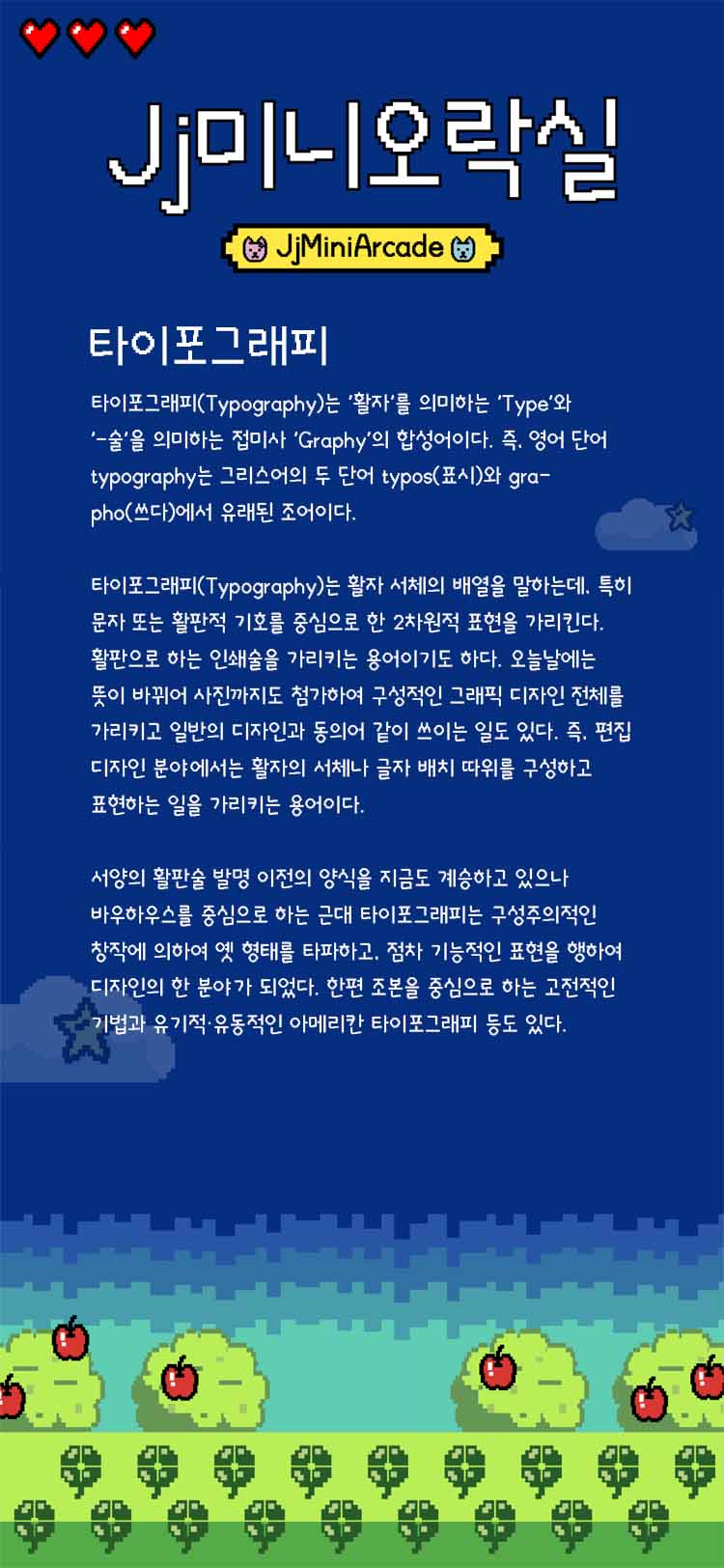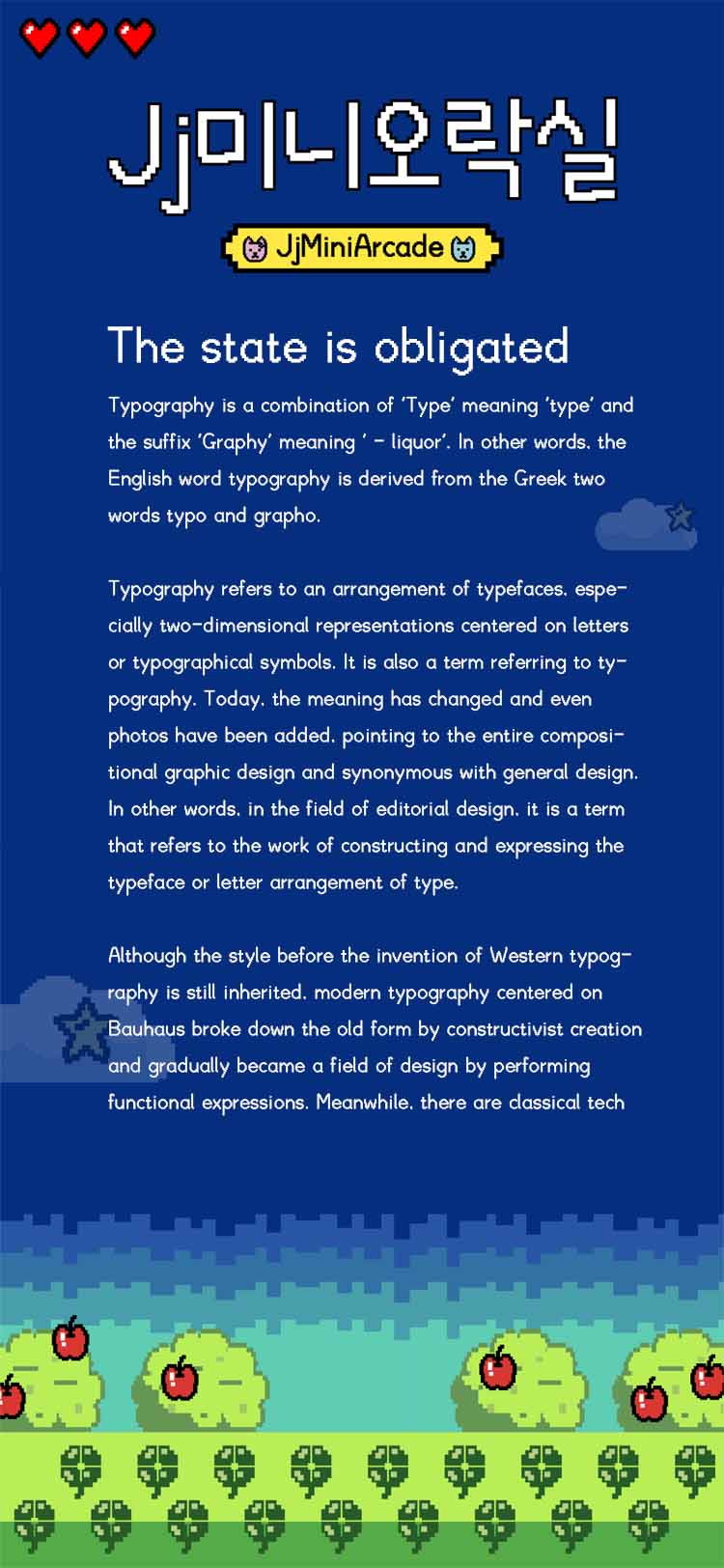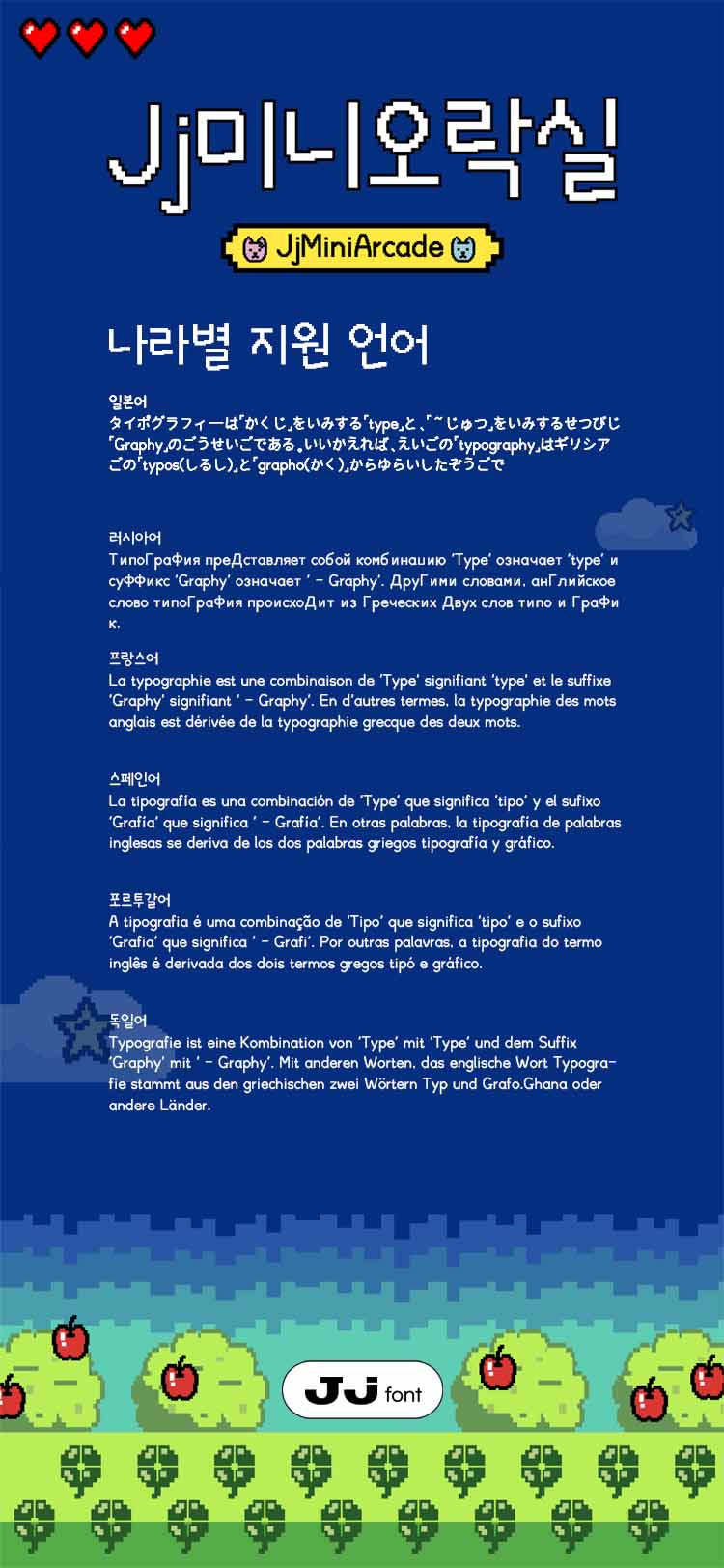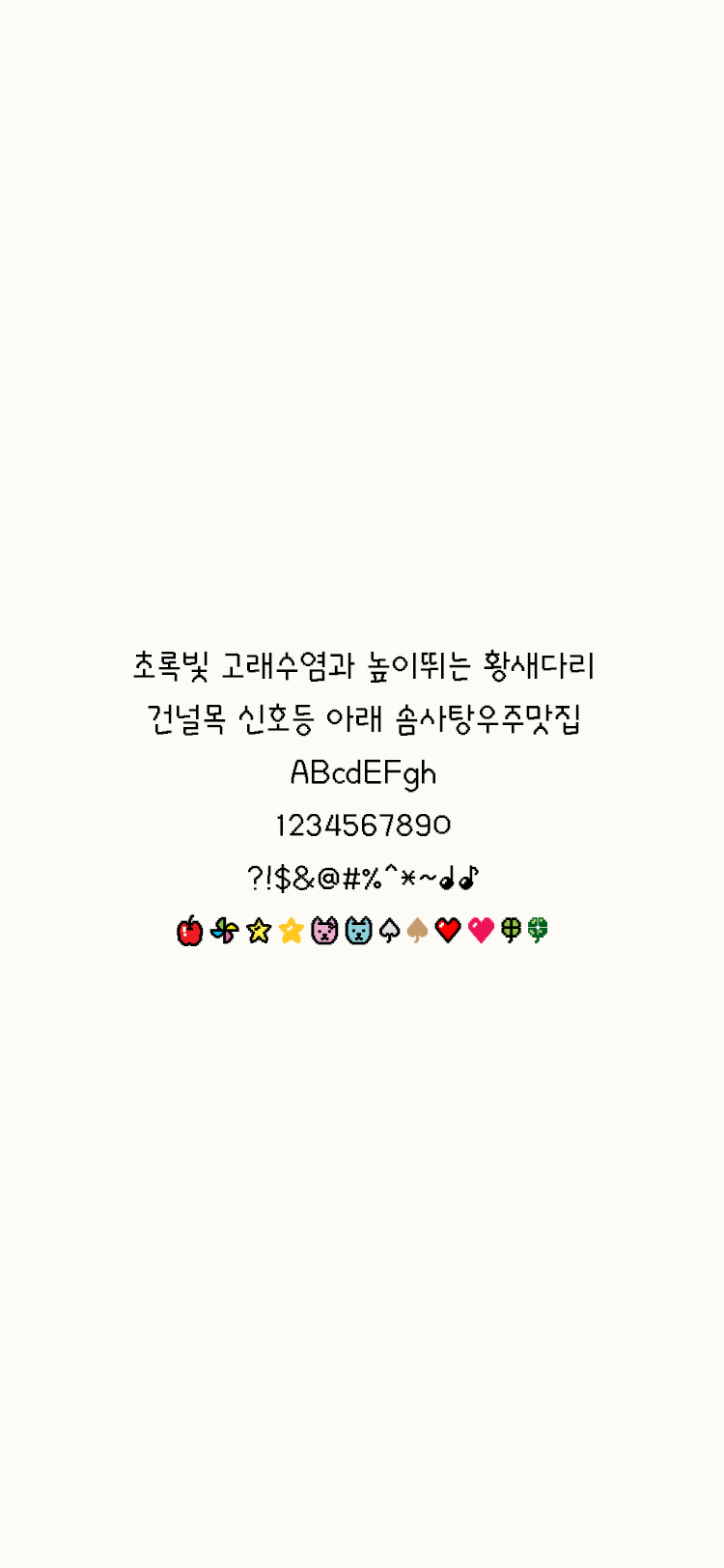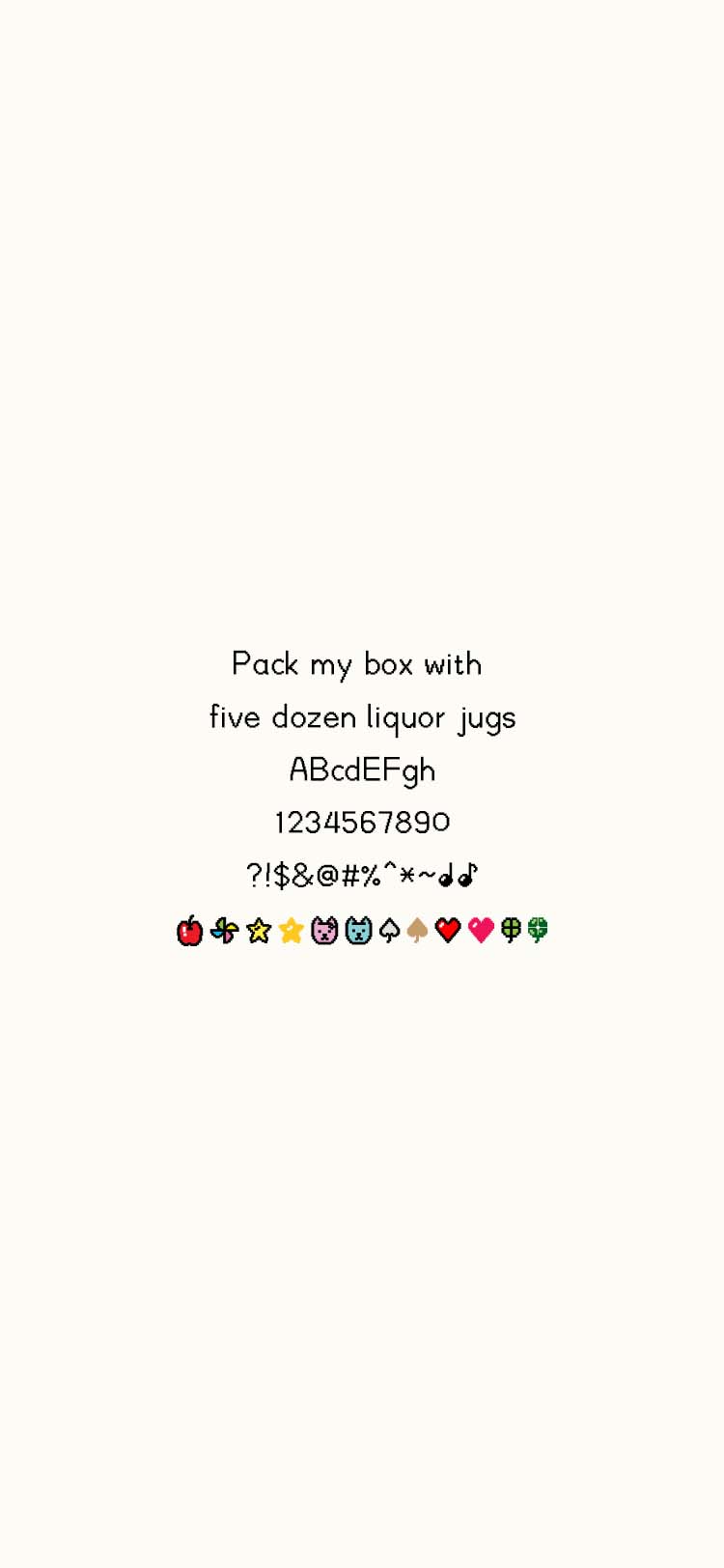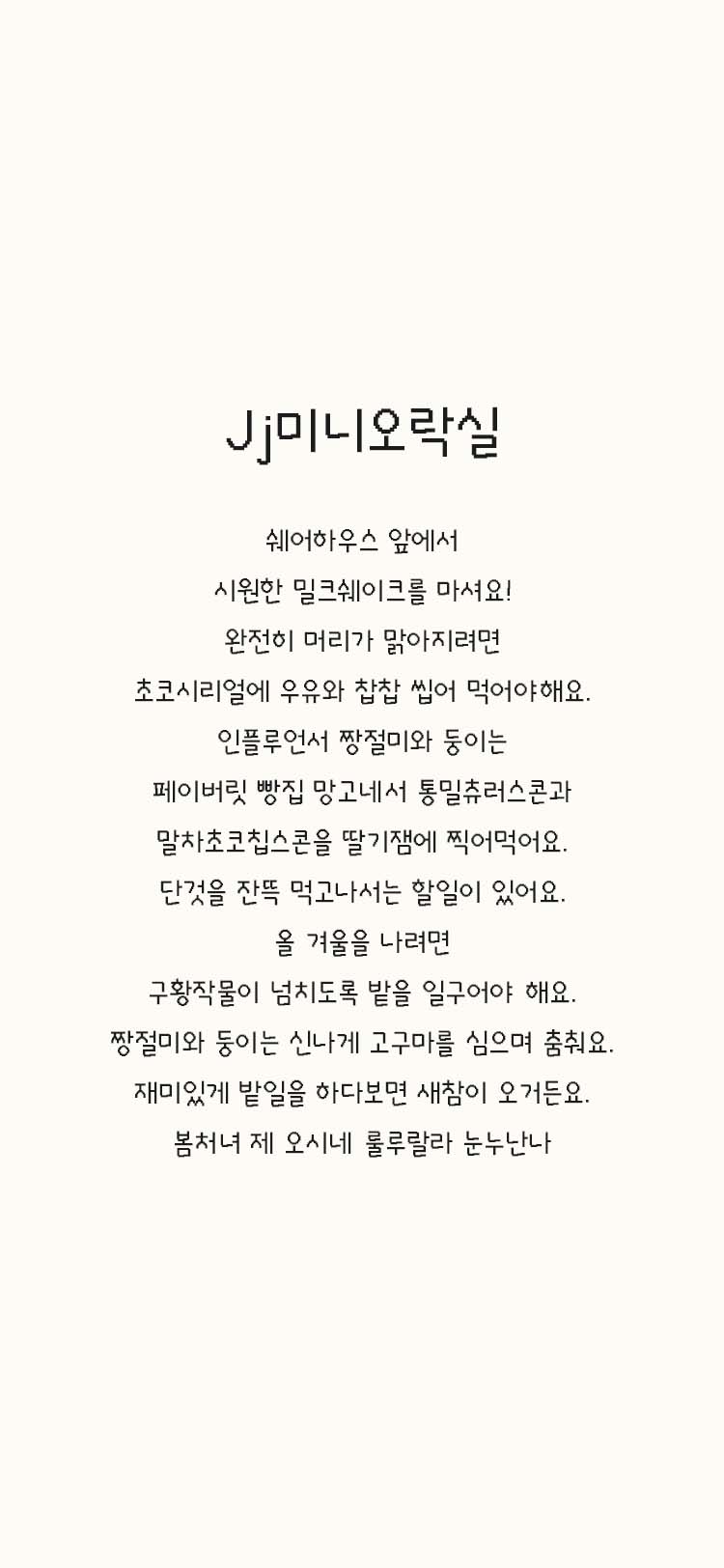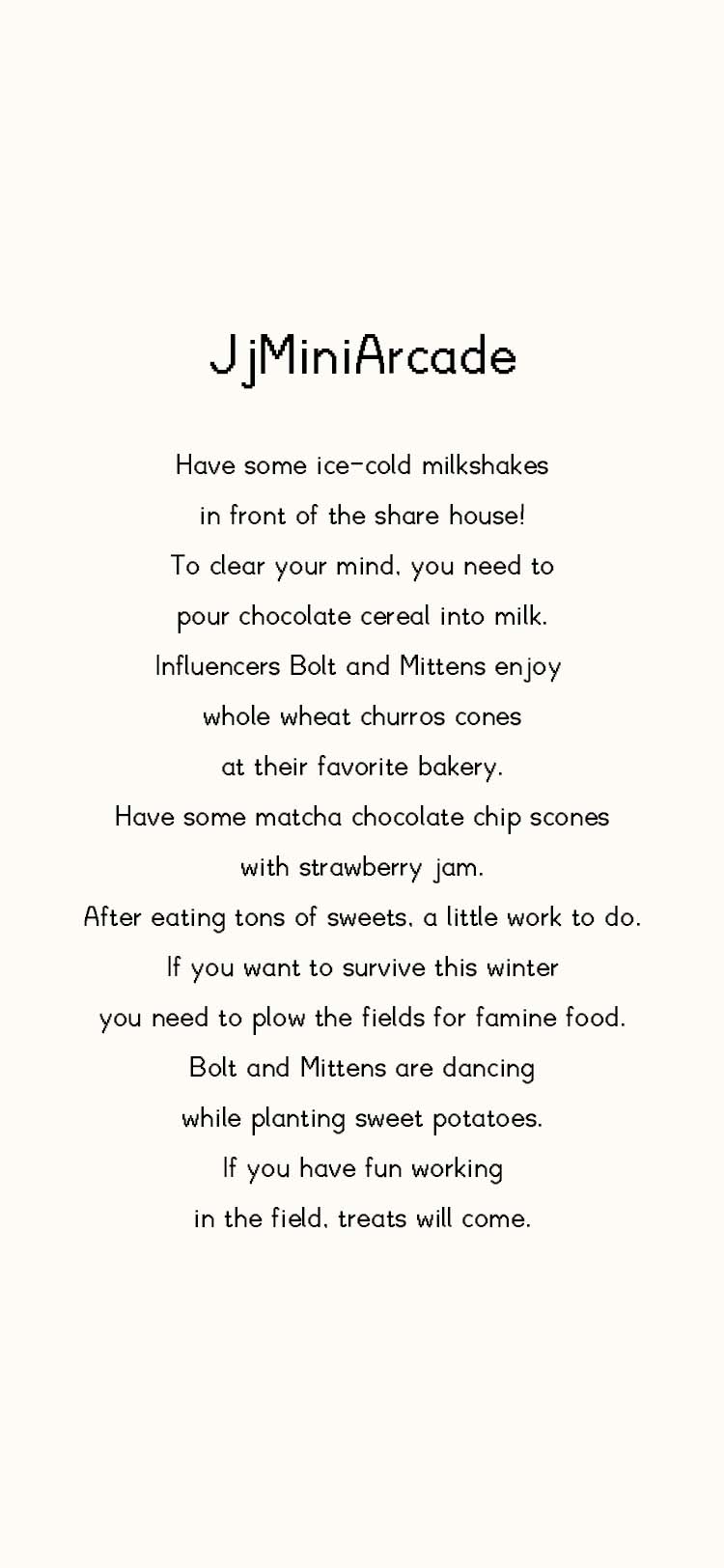
Jj미니오락실로 바꾼 ㄴㅐㄱㅏ 좋ㄷㅏ…☆”
Jj미니오락실은 추억을 담은 캐쥬얼한 비트맵폰트입니다.
- ;), ;> 을 치면 기쁨과 신남과 있어요.
- ♂♀♡♥♤♠♧♣에서 컬러 딩벳을 지원합니다.
- 라틴, 일본어(히라가나, 카타카나), 키릴문자를 지원합니다,.
- 한글 11,172자 / 라틴 95자 / 부호 985자
- Jj미니오락실 / JjMiniArcade